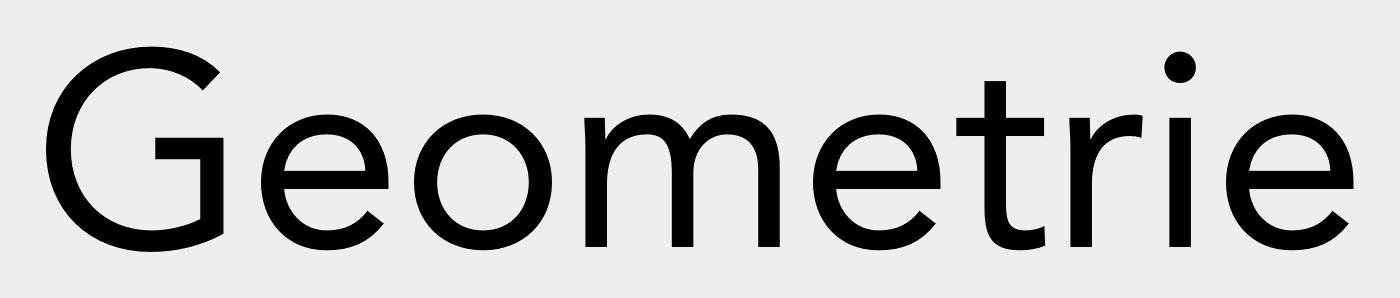
Welche Grotesk zur FF Scala?
Kann mir jemand eine Grotesk empfehlen, die zur FF Scala passt UND die auf dem Mac (OS X, Adobe CS6 Font Folio) vorinstalliert ist?
Ich suche eine neutrale, aber nicht zu abgedroschene Grotesk, kann aber leider nicht extra Geld bzw. nicht mehr als 35 EUR ausgeben (ansonsten würde ich die FF Scala Sans kaufen).
Ich soll einen Katalog für einen Künstler erstellen, der sehr bunt, abstrakt, mit vielen geometrischen Formen und mit Strukturen malt.
Würden zur Not die Helvetica oder Futura o. ä. passen?
Am Ende ist es auch Geschmacksache, ich weiß. Irgendwie ist meiner mir aber gerade nicht verfügbar. ;-) Also vielleicht habt Ihr Tipps?
Oder beide zusammen*:
… ist bei macOS dabei :nicken:
*) Nicht wirklich, ich weiß
;-) Aber ein Zwitter ist es ja trotzdem